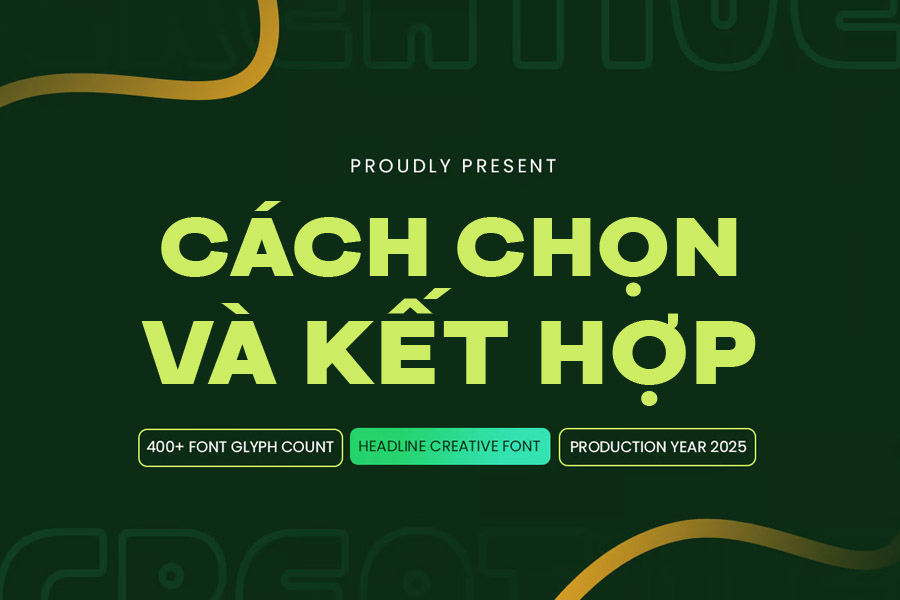
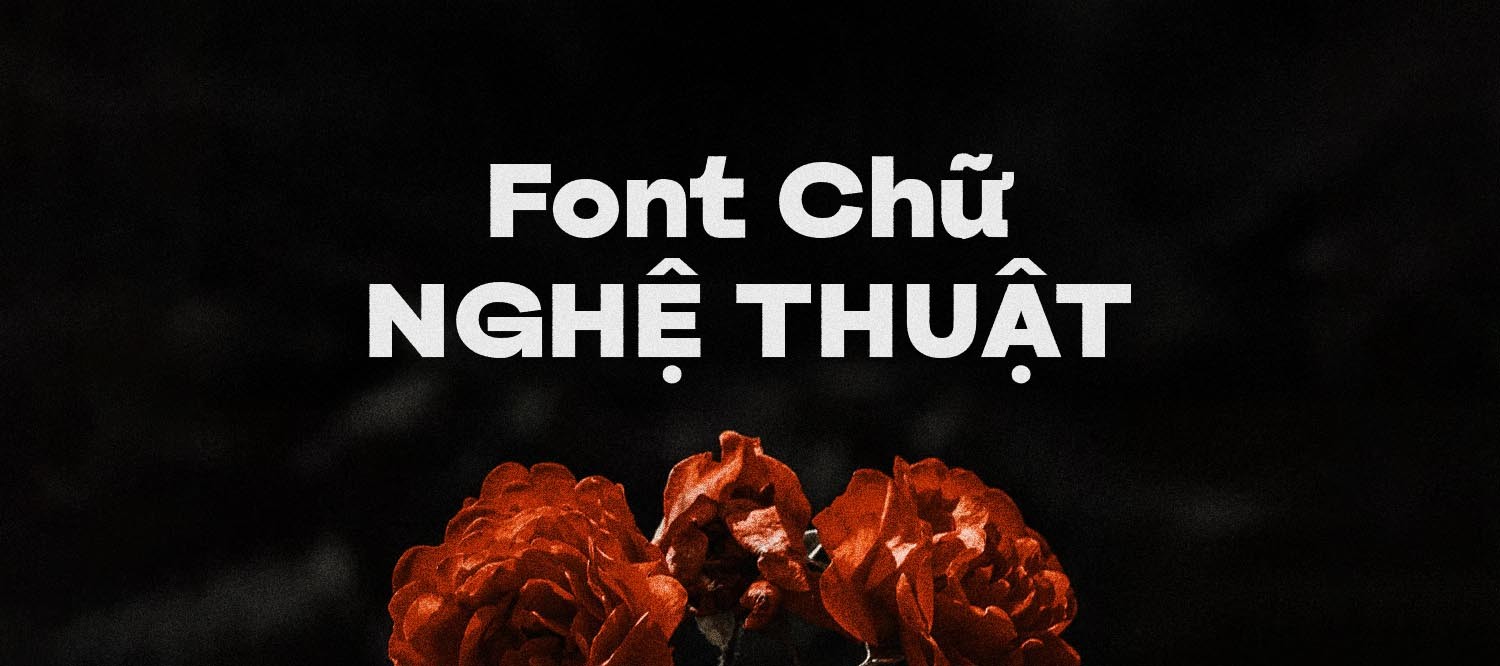
Font chữ nghệ thuật là các phông chữ được thiết kế để mang đến một sự sáng tạo, độc đáo và khác biệt so với các font chữ thông thường. Những font này không chỉ phục vụ mục đích truyền tải thông điệp, mà còn là một phần quan trọng trong việc tạo nên phong cách, cá tính cho một sản phẩm thiết kế.
Trong thiết kế đồ họa, font chữ nghệ thuật có khả năng gây ấn tượng mạnh mẽ đối với người xem, giúp sản phẩm thiết kế trở nên nổi bật và thu hút sự chú ý. Font chữ nghệ thuật không chỉ là công cụ truyền tải thông tin, mà còn góp phần định hình thương hiệu, tạo dựng hình ảnh cho các chiến dịch marketing.
Font chữ nghệ thuật đã xuất hiện từ rất lâu và phát triển mạnh mẽ trong những năm gần đây nhờ vào sự đổi mới trong công nghệ thiết kế. Ban đầu, chúng chủ yếu được sử dụng trong các ấn phẩm in ấn, poster quảng cáo. Ngày nay, với sự phát triển của phần mềm thiết kế, font chữ nghệ thuật ngày càng được ứng dụng rộng rãi trong mọi lĩnh vực thiết kế từ in ấn đến thiết kế số.
Dưới đây là danh sách 15 font chữ nghệ thuật mới nhất bạn có thể tải về và sử dụng cho các dự án thiết kế:
Font chữ dễ thương, mang đậm phong cách cute và tươi mới, phù hợp cho thiết kế thiệp mời, bao bì sản phẩm hoặc trang trí các dự án dành cho trẻ em. Các đường nét mềm mại, nhẹ nhàng giúp dễ dàng thu hút người nhìn.
Font chữ viết tay mang lại sự mềm mại và nhẹ nhàng, lý tưởng cho các thiết kế mang tính cá nhân như thư tay, thiệp chúc mừng hoặc các sản phẩm thủ công. Các đường nét uyển chuyển giúp tạo nên một phong cách độc đáo và thân thiện.
Được thiết kế với phong cách serif thanh lịch, font này mang đến vẻ đẹp tinh tế, hoàn hảo cho các dự án cao cấp như thiệp cưới, logo sang trọng hoặc các bài viết trang trọng. Các đường nét sắc sảo mang lại sự ấn tượng mạnh mẽ cho thiết kế của bạn.
Font chữ dễ thương với các đường cong mềm mại, mang lại sự ấm áp cho các thiết kế liên quan đến tình yêu, thiệp cưới hoặc các sản phẩm lãng mạn. Các chi tiết trái tim nhỏ xinh làm cho font này trở thành lựa chọn tuyệt vời cho những dịp đặc biệt.
Mang phong cách viết tay mềm mại, lãng mạn, Romantic Heart là sự lựa chọn hoàn hảo cho các thiết kế tình yêu, lễ hội hoặc thiệp mừng. Các chi tiết trái tim và đường nét uốn lượn mang lại sự ấm áp và dễ thương, phù hợp với các sự kiện đặc biệt như Valentine hay sinh nhật.
Với các đường nét mượt mà và thanh thoát, Buttain là sự kết hợp giữa sự hiện đại và cổ điển, tạo điểm nhấn mạnh mẽ cho các thiết kế cần sự duyên dáng và tinh tế. Font này thích hợp cho thiệp cưới, thư mời, hoặc các sản phẩm mang tính cá nhân.
Phong cách viết tay thanh lịch và sang trọng của Griffiths mang lại sự quý phái cho các thiết kế cao cấp. Font này rất phù hợp cho thiệp cưới, danh thiếp hoặc các dự án cần sự tinh tế và nổi bật, làm tôn lên vẻ đẹp của từng từ ngữ trong thiết kế.
Được thiết kế với phong cách thư pháp cổ điển, Thư Pháp Đức Thủy là lựa chọn lý tưởng cho các dự án cần sự tinh tế và sang trọng. Font này rất phù hợp cho thiệp cưới, thiệp mời hoặc các sản phẩm nghệ thuật cần sự trang nhã và thanh thoát.
Mang phong cách thư pháp uyển chuyển và thanh thoát, FZ Tiểu Tứ rất thích hợp cho các thiết kế mang đậm tính văn hóa truyền thống như thiệp cưới, thư mời hoặc các sản phẩm trang trí. Các đường nét mềm mại tạo cảm giác gần gũi và lãng mạn.
Font chữ Chicanos mang phong cách calligraphy mạnh mẽ và phóng khoáng, rất phù hợp cho các thiết kế cần sự cá tính, nổi bật như poster âm nhạc, áo thun hoặc logo. Sự kết hợp giữa nét mạnh mẽ và mềm mại tạo ra một font chữ đầy sức hút và độc đáo.
Geraldyne là font chữ viết tay thanh thoát, phù hợp cho các thiết kế cần sự mềm mại và lãng mạn. Các đường nét uyển chuyển tạo nên một phong cách gần gũi và tinh tế, rất thích hợp cho thiệp cưới, thư mời và các sản phẩm thủ công mang tính cá nhân.
TH Culture mang đậm phong cách hoài cổ, rất thích hợp cho các thiết kế mang đậm giá trị văn hóa truyền thống, đặc biệt là các dịp lễ Tết, sự kiện văn hóa hoặc các sản phẩm trang trí cổ điển. Các đường nét mạnh mẽ nhưng vẫn giữ được sự mềm mại, tạo sự ấn tượng đặc biệt cho thiết kế.
LNTH Daybreaker mang đậm phong cách truyền thống, với các đường nét mạnh mẽ và sắc sảo, rất phù hợp cho các thiết kế có chủ đề văn hóa truyền thống, như banner, quảng cáo hoặc các sản phẩm trang trí có yếu tố lịch sử.
Zahra là font chữ mang phong cách cổ trang, rất thích hợp cho các thiết kế mang đậm yếu tố truyền thống và cổ điển. Các đường nét mềm mại kết hợp với các chi tiết sắc sảo giúp tạo ra một thiết kế thanh thoát và sang trọng, rất phù hợp cho thiệp cưới, Tết hoặc các sản phẩm văn hóa.
Không phải lúc nào font chữ nghệ thuật cũng phù hợp. Chúng nên được chọn cho những thiết kế cần sự nổi bật và cá tính.
Font chữ nghệ thuật có thể thay thế font tiêu chuẩn trong một số trường hợp, nhưng cần đảm bảo tính chuyên nghiệp và dễ đọc.
Font chữ nghệ thuật mang đến sự sáng tạo và cá tính trong thiết kế. Việc chọn đúng font giúp dự án thiết kế của bạn nổi bật và dễ dàng gây ấn tượng với người xem. Hãy đảm bảo rằng bạn chọn font chữ phù hợp với mục đích và thông điệp thiết kế của mình.